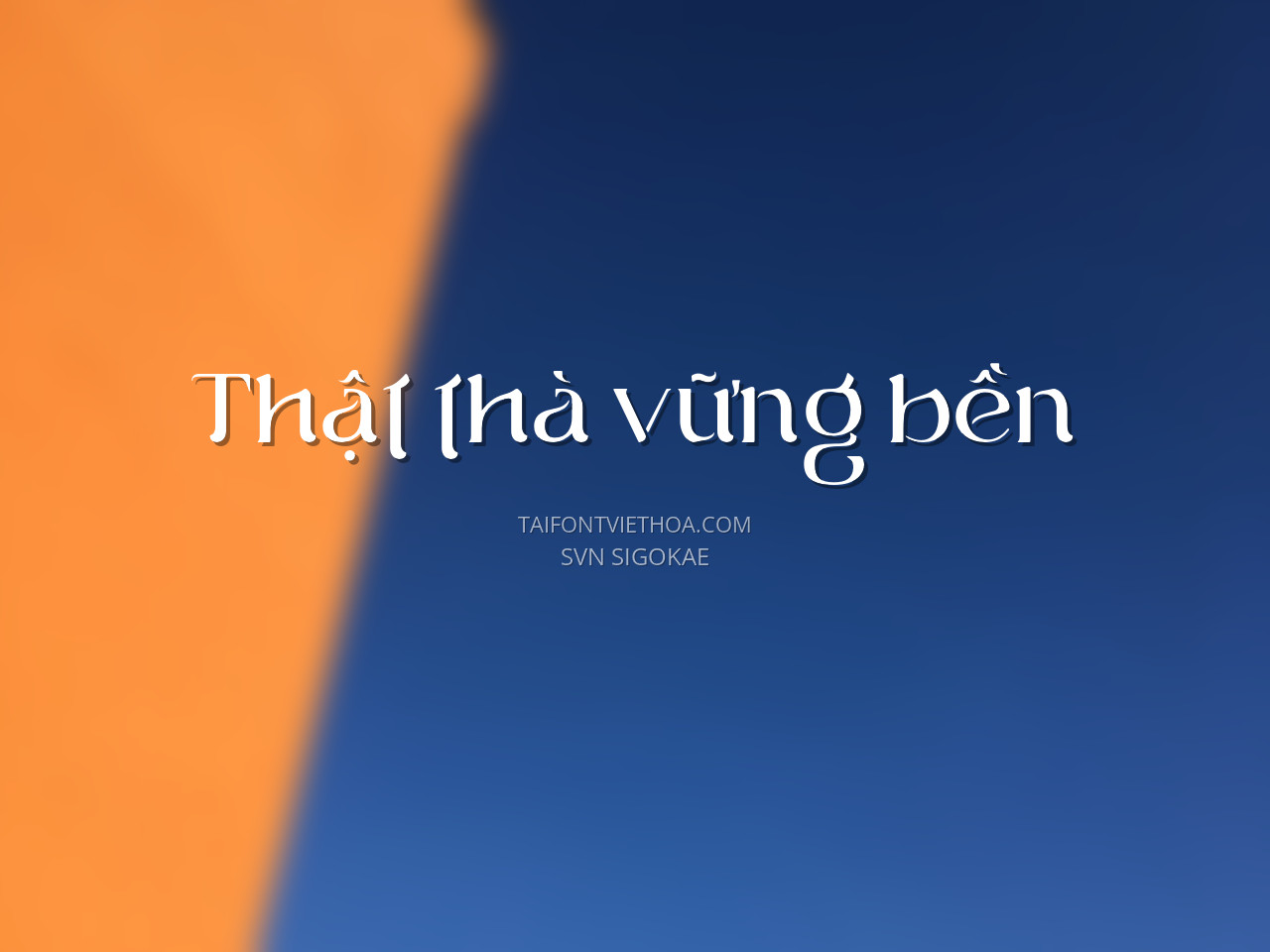
Font việt hóa SVN Sigokae
Giới thiệu về Sigokae – Font handwritten cá tính, đậm chất Hàn Quốc
Sigokae (tên gốc: Sigokae Typeface) là phông chữ viết tay (handwritten) mang hơi thở hiện đại, được thiết kế bởi Gunarta(Indonesia) và phát hành trên Creative Market từ năm 2020. Font lấy cảm hứng từ phong cách chữ viết tay Hàn Quốc, với các đường nét tự nhiên, phóng khoáng, kết hợp yếu tố tinh nghịch nhưng vẫn hài hòa, dễ đọc. Phiên bản quốc tế của Sigokae hỗ trợ trên 60 ngôn ngữ Latin, sở hữu bộ ký tự đặc biệt, alternates, ligature đầy đủ, phù hợp cho nhiều mục đích thiết kế sáng tạo – từ digital đến in ấn truyền thống.
Bản SVN Sigokaeđã được STYLEno.1 FontsViệt hóa đầy đủ: bổ sung dấu tiếng Việt, căn chỉnh kerning, tối ưu hóa hinting để hiển thị sắc nét trên cả màn hình lẫn in ấn. Đội ngũ taifontviethoa.comđã trực tiếp kiểm thử thực tế trên Photoshop, Illustrator, Canva…, đảm bảo không lỗi dấu, không vỡ nét, sẵn sàng sử dụng cho các dự án cá nhân, branding, poster nghệ thuật hoặc các ấn phẩm quảng cáo trẻ trung, hiện đại.
Đặc điểm thiết kế, ứng dụng và ngành nghề phù hợp
Sigokae thuộc nhóm viết tay (handwritten)với nét chữ tự nhiên, bo tròn nhẹ, spacing thoáng đãng và nhịp điệu sinh động, tạo cảm giác gần gũi, trẻ trung. Các alternates, ligature đa dạng cho phép cá nhân hóa tiêu đề, poster, logo, thiệp mời hoặc các sản phẩm handmade. Sigokae phát huy hiệu quả khi dùng trong các thiết kế branding, story social media, thiệp mời, ấn phẩm nghệ thuật hay bao bì sản phẩm sáng tạo.
Ứng dụng tiêu biểu
Sigokae là lựa chọn tuyệt vời cho các ngành quảng cáo, sáng tạo, handmade, thời trang, beauty, giáo dục, tổ chức sự kiện… Khi kết hợp với các font sans-serif, Sigokae giúp tổng thể thiết kế trẻ trung, cá tính và gần gũi hơn. Tải ngay bản Việt hóa tại taifontviethoa.com để trải nghiệm trọn bộ glyph cho mọi dự án sáng tạo của bạn.